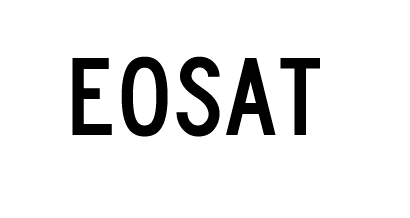
Suche Ersatz und Ergänzung zur 'Lane B'
ich suche zu der 'Lane B'
einen Font der leicht fetter im Schnitt wäre.
Und Schriften die auch sonst passen könnten. Unsicherheiten mit meiner Auswahl.
hm, vielleicht mal die Interstate Condensed anschauen, die gibt es in verschiedenen Fetten.